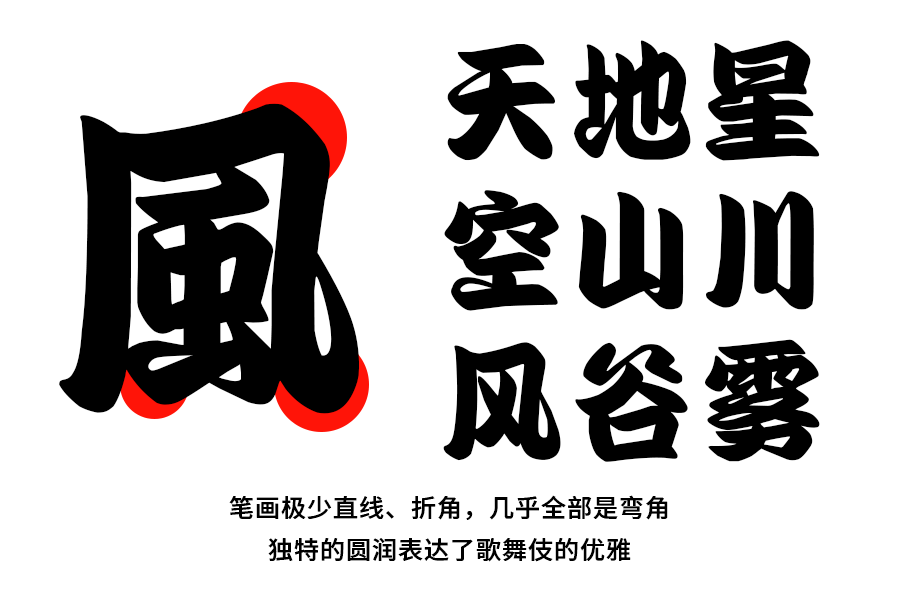
勘亭流(かんていりゅう)是使用最广泛也是最常见的江户文字,又被称为“芝居文字”,在日本街头随处可见。它最早是用于落语(类似中国的单口相声)、歌舞伎等的招牌或节目表的字体。由戏剧界人物冈崎屋勘六设计,勘亭流就是得名自其别号“勘亭”。
勘亭流体是笔画厚实、膨胀、风格化的写法,用刷子书写并向内弯曲,笔画回转内收。字形圆润、敦厚,笔画中极少出现直线与折角,几乎全由曲线和弯角构成。
在现代,勘亭流风格的文字在日本的使用范围也很广泛,例如剧本和演员更衣室的展示,以及剧院前面的标志和街上广告、海报。